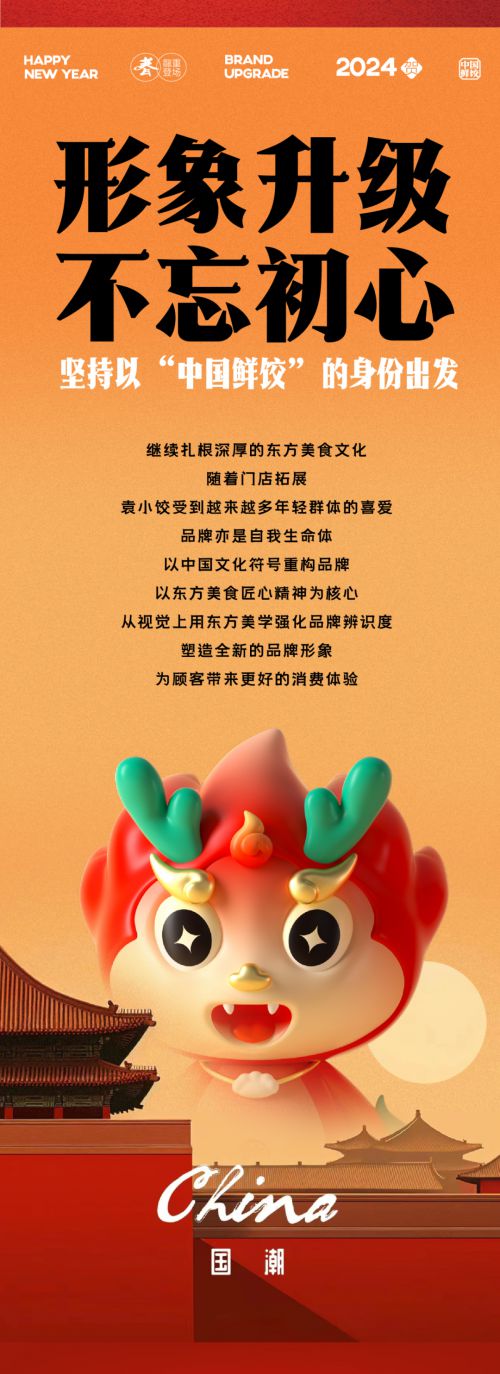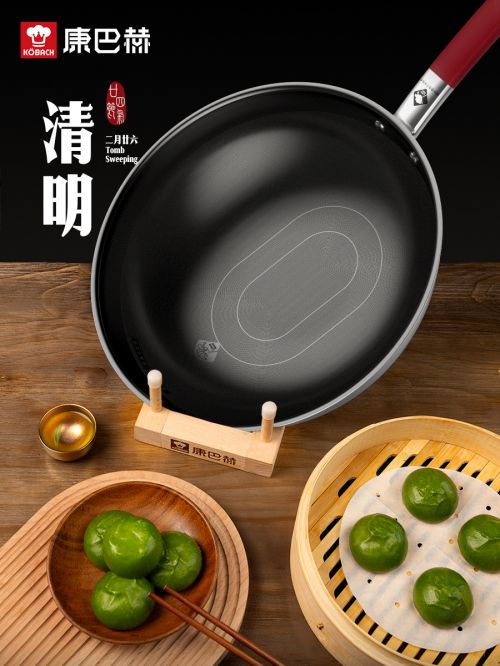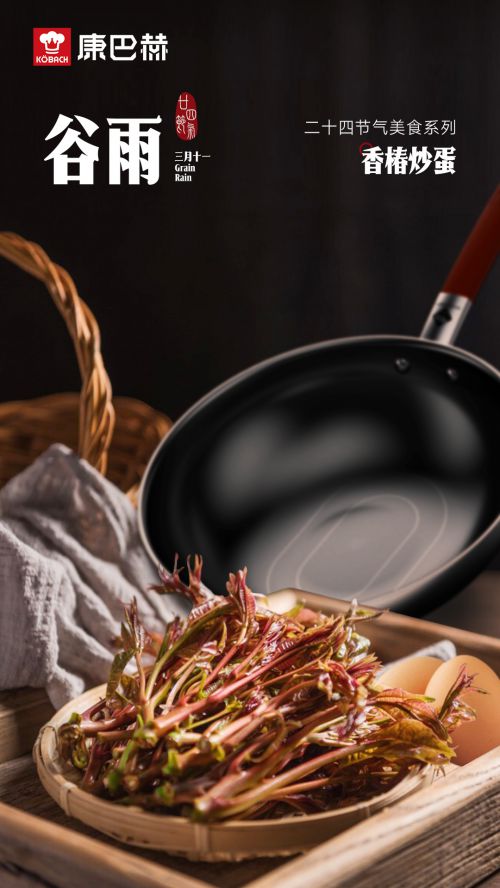
点字俊然宋
点字俊然宋是一款带有复古风的标题宋体字。有宋体字稳定的结构,笔锋加入鹅头设计,将复古式字形与现代化宋体完美的结合于一体,点字俊然宋适用于各类商业广告、游戏海报、公司标准字、包装、公司口号、淘宝电商、网站宣传等……
石凯
90后字体设计师,字由文案一哥。字体圈里段子写的最好的,段子手中字体设计最棒的。